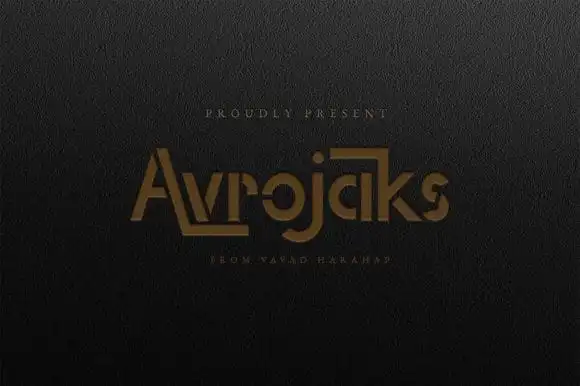
Avrojaks Display Font – Download Grátis
A Avrojaks Display Font é uma poderosa tipografia tecnologia futurista com forte presença visual e estilo moderno. Desenvolvida por VavadHarahap, ela traz um conceito minimalista e distintivo para seu gênero de fontes em formato de exibição. Esta elegante tipografia não apenas oferece uma aparição clean e limpa, mas também adiciona um toque de sofisticação a qualquer projeto. Perfeita para ambientes onde a simplicidade criativa se encaixa perfeitamente com o respeito pelo design moderno, a Avrojaks Display Font é perfeita para aqueles que valorizam uma fonte única e atemporal. Seja em um layout de página ou em um poster de mídia social, a Avrojaks Display Font certamente dará o seu toque diferenciado à sua ideia criativa.